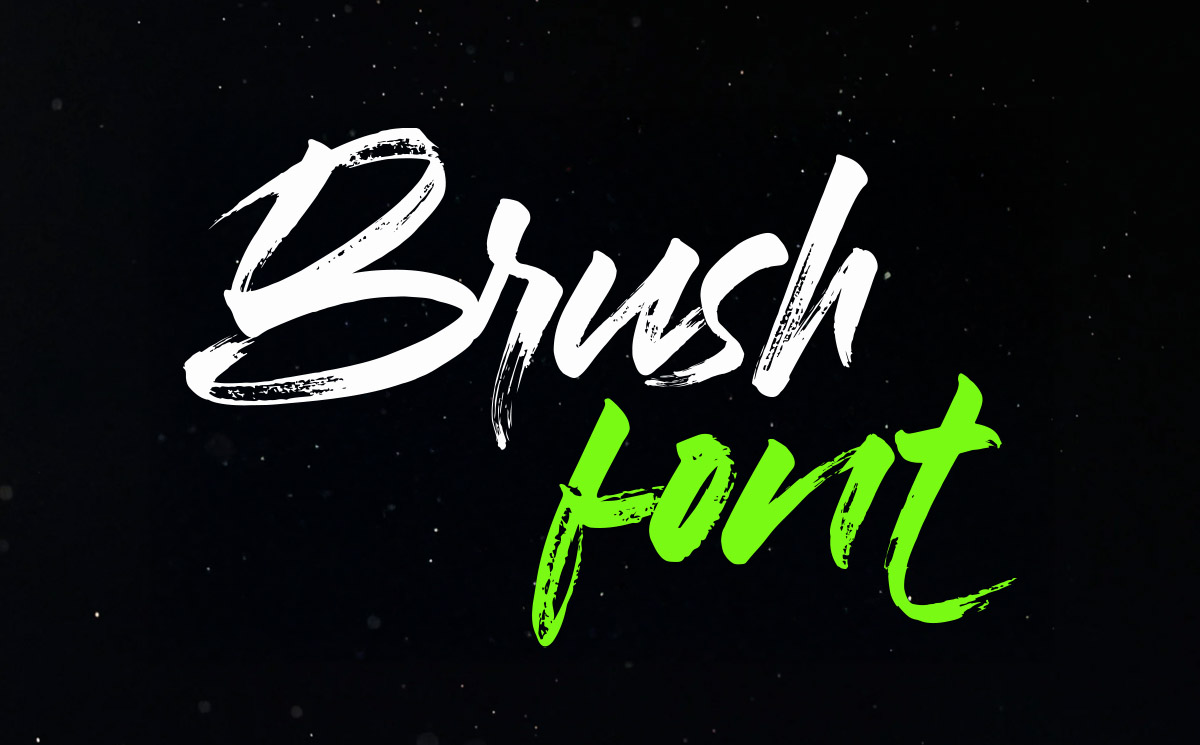
Font chữ nghiêng brush nét cọ Việt hóa SVN-Braga
Font chữ nghiêng brush nét cọ Việt hóa SVN-Braga là giải pháp phông chữ nghệ thuật tuyệt vời dành cho các nhà thiết kế đang tìm kiếm sự phóng khoáng, hiện đại và đầy cá tính. Với các đường nét cọ xước chân thực kết hợp cùng dáng chữ nghiêng mượt mà, bộ font này giúp truyền tải cảm xúc mạnh mẽ và tạo điểm nhấn thị giác độc đáo cho mọi sản phẩm truyền thông. Phiên bản Việt hóa trọn bộ giúp bạn thỏa sức sáng tạo mà không còn lo ngại về vấn đề lỗi font hay thiếu dấu tiếng Việt.
Font Chữ Nghiêng Brush Nét Cọ Việt Hóa SVN-Braga – Đỉnh Cao Phông Chữ Nghệ Thuật Cho Thiết Kế Bứt Phá
Trong thế giới thiết kế đồ họa hiện đại, việc lựa chọn một bộ phông chữ vừa mang tính nghệ thuật cao, vừa thể hiện được cái tôi sáng tạo là yếu tố quyết định sự thành công của một ấn phẩm. Font chữ nghiêng brush nét cọ Việt hóa SVN-Braga chính là một trong những kiệt tác typographic được giới thiết kế săn đón hàng đầu. Mang phong cách thư pháp hiện đại (modern calligraphy) kết hợp với kỹ thuật vẽ cọ khô (dry brush style), SVN-Braga tạo nên sự cân bằng hoàn hảo giữa nét mềm mại, uyển chuyển và sự góc cạnh, tự do.
Việc bộ font này được Việt hóa chuẩn xác theo chuẩn Unicode giúp cộng đồng sáng tạo tại Việt Nam dễ dàng ứng dụng vào các dự án thương mại cũng như cá nhân. Từ thiết kế nhận diện thương hiệu, bao bì sản phẩm, banner quảng cáo cho đến thiệp mời sự kiện, SVN-Braga đều hoàn thành xuất sắc nhiệm vụ tôn vinh thông điệp mà nhà thiết kế muốn truyền tải.
1. Đường Nét Cọ Xước Tự Nhiên Và Dáng Chữ Nghiêng Đầy Năng Lượng
Điểm đặc trưng ấn tượng nhất của SVN-Braga chính là hiệu ứng nét cọ thủ công sống động. Mỗi ký tự đều được chăm chút tỉ mỉ với các chi tiết cọ xước (texture) mượt mà, gợi liên tưởng đến những vệt sơn cọ còn chưa kịp khô trên nền giấy thô. Góc nghiêng tiêu chuẩn của chữ tạo ra cảm giác chuyển động linh hoạt, giúp câu từ trở nên có nhịp điệu và giàu sức sống hơn hẳn các font chữ tĩnh thông thường.
Hiệu ứng này không chỉ mang lại tính thẩm mỹ cao mà còn giúp ấn phẩm thiết kế thoát khỏi sự cứng nhắc, thô ráp. Khi ứng dụng SVN-Braga vào các tiêu đề lớn (headlines) hay các câu khẩu hiệu (slogans), bộ font sẽ ngay lập tức thu hút thị giác của người xem, giữ chân họ lâu hơn trên thiết kế của bạn.
2. Tối Ưu Hóa Tiếng Việt Chuẩn Xác Không Lỗi Dấu
Một trong những rào cản lớn nhất khi sử dụng các phông chữ brush quốc tế là vấn đề lỗi font khi gõ tiếng Việt. Với bản Việt hóa SVN-Braga, toàn bộ hệ thống dấu thanh (sắc, huyền, hỏi, ngã, nặng) và các ký tự đặc trưng của tiếng Việt (ă, ê, ô, ơ, ư, đ) đều được thiết kế lại một cách tỉ mỉ. Các dấu thanh được đặt ở vị trí cân đối, tỷ lệ cọ tương thích hoàn hảo với thân chữ chính, đảm bảo tính thẩm mỹ tổng thể không bị phá vỡ.
Nhờ quy trình Việt hóa chỉn chu, người dùng có thể thoải mái soạn thảo các đoạn văn bản tiếng Việt giàu biểu cảm mà không sợ xuất hiện các ký tự bị lỗi hiển thị hay mất nét. Điều này tiết kiệm đáng kể thời gian chỉnh sửa thủ công cho các designer trong quá trình làm việc.
3. Bộ Ký Tự Mở Rộng Phong Phú Với Ligatures Và Swashes Nối Chữ
Font SVN-Braga không dừng lại ở các ký tự chữ cái cơ bản. Nhà sản xuất và đơn vị Việt hóa đã tích hợp hệ thống ký tự thay thế (alternates), các nét nối chữ (ligatures) và nét uốn đuôi chữ (swashes) vô cùng đa dạng. Tính năng này cho phép bạn biến hóa từng từ ngữ theo phong cách riêng, tạo nên những đường nét uốn lượn mang đậm dấu ấn cá nhân giống như được viết tay trực tiếp.
• Ligatures thông minh: Tự động kết hợp các cặp chữ cái liền kề để tạo ra dòng chảy chữ tự nhiên và liền mạch.
• Swashes nghệ thuật: Các nét móc uốn lượn ở đầu hoặc cuối từ giúp điểm xuyết cho tiêu đề thêm phần bay bổng và sang trọng.
• Glyphs đa dạng: Cung cấp nhiều biến thể của cùng một chữ cái, giúp thiết kế không bị lặp lại đơn điệu.
4. Tính Ứng Dụng Đa Năng Trong Nhiều Lĩnh Vực Thiết Kế
Nhờ sự kết hợp độc đáo giữa tính hiện đại và nét thủ công mộc mạc, SVN-Braga là sự lựa chọn linh hoạt cho rất nhiều phong cách thiết kế khác nhau. Bạn có thể dễ dàng ứng dụng font chữ này vào:
1. Thiết kế nhận diện thương hiệu: Tạo logo, tagline cho các thương hiệu thời trang, mỹ phẩm, spa, quán cafe hay phong cách sống (lifestyle).
2. Ấn phẩm truyền thông & Quảng cáo: Poster phim, banner sự kiện, cover album ca nhạc, hình ảnh bài đăng mạng xã hội (Facebook, Instagram, TikTok).
3. In ấn & Bao bì: Thiệp cưới phong cách Rustic/Vintage, nhãn mác sản phẩm thủ công, bìa sách, áo thun typographic.
4. Trích dẫn nghệ thuật (Quotes): Lời hay ý đẹp, trích dẫn truyền cảm hứng trên nền ảnh nghệ thuật.